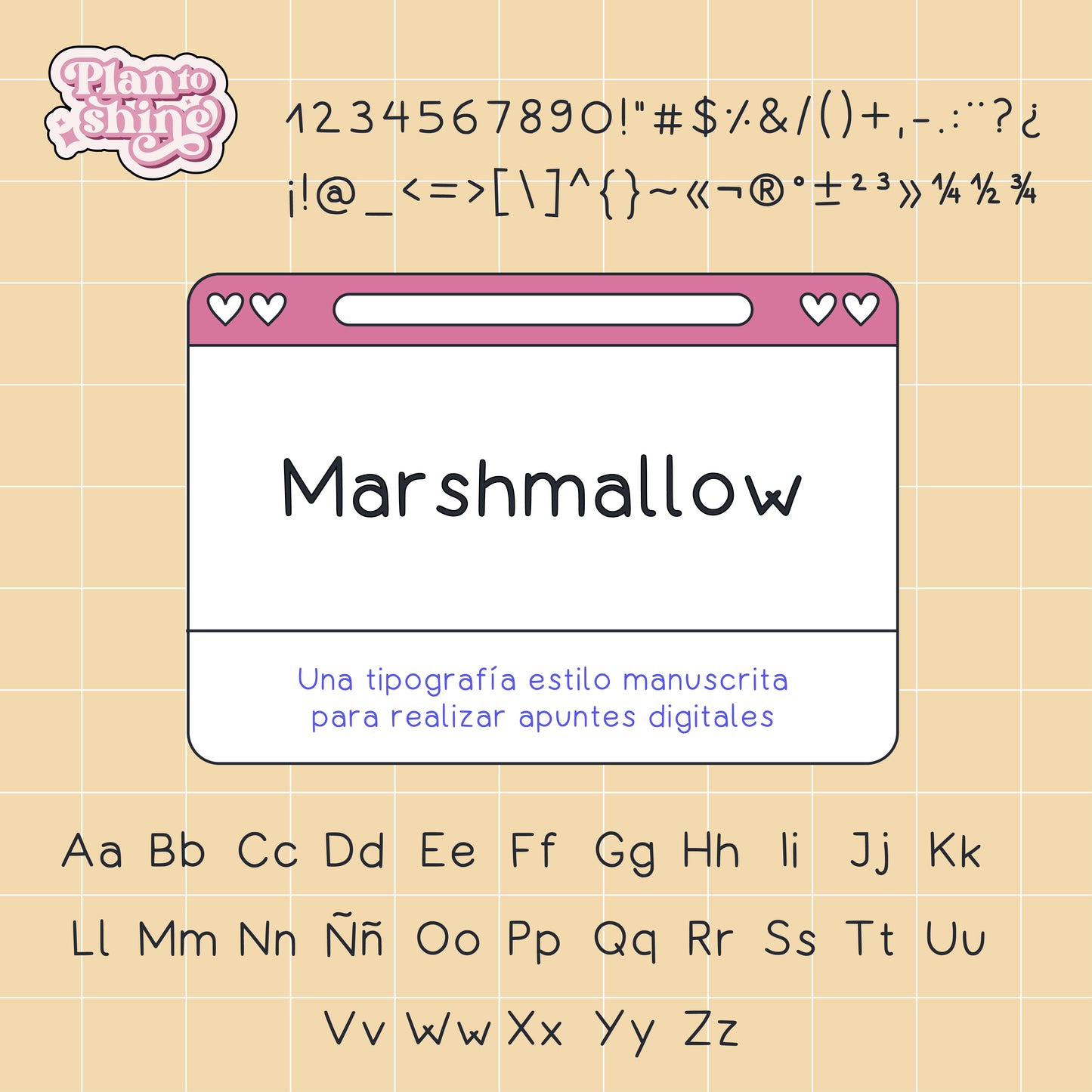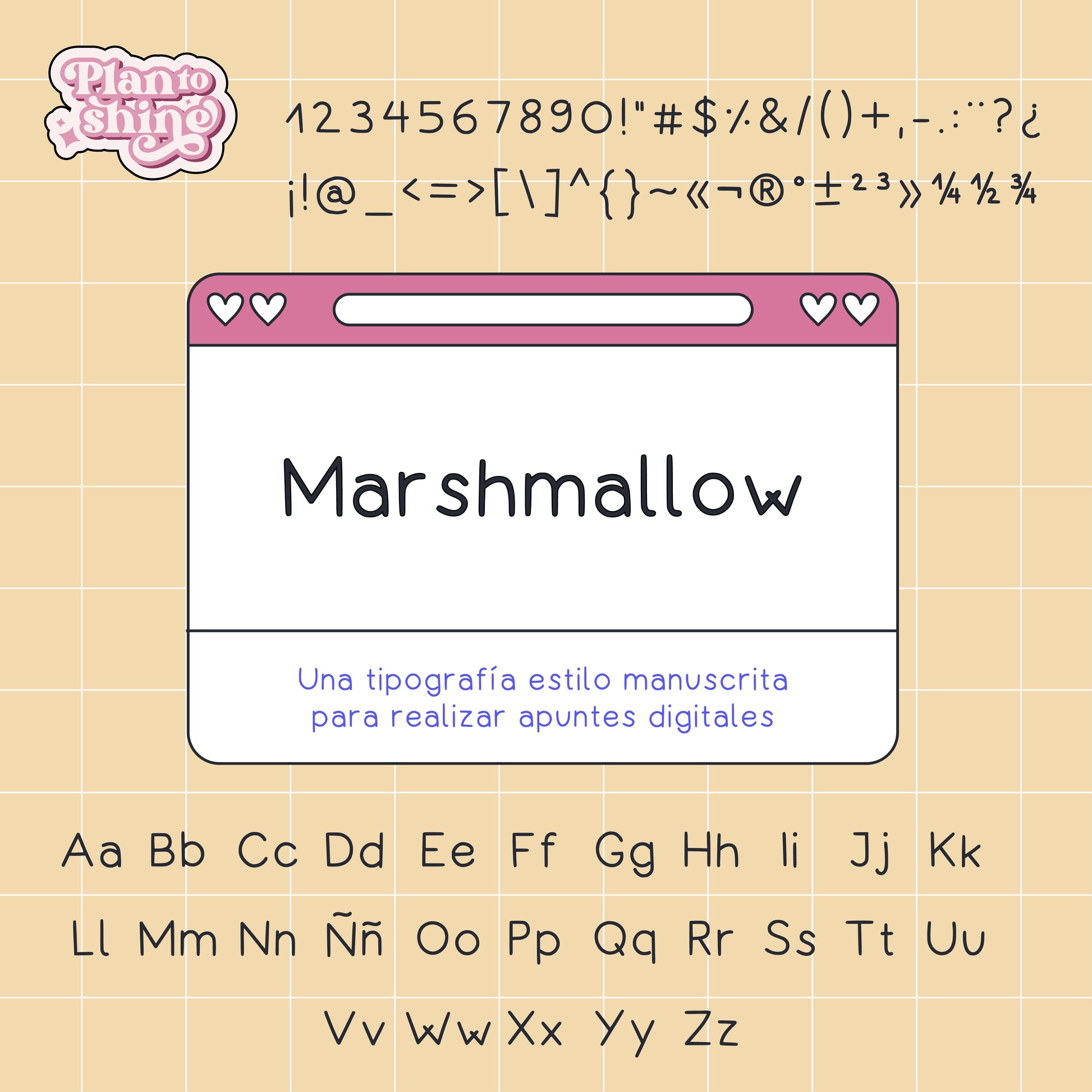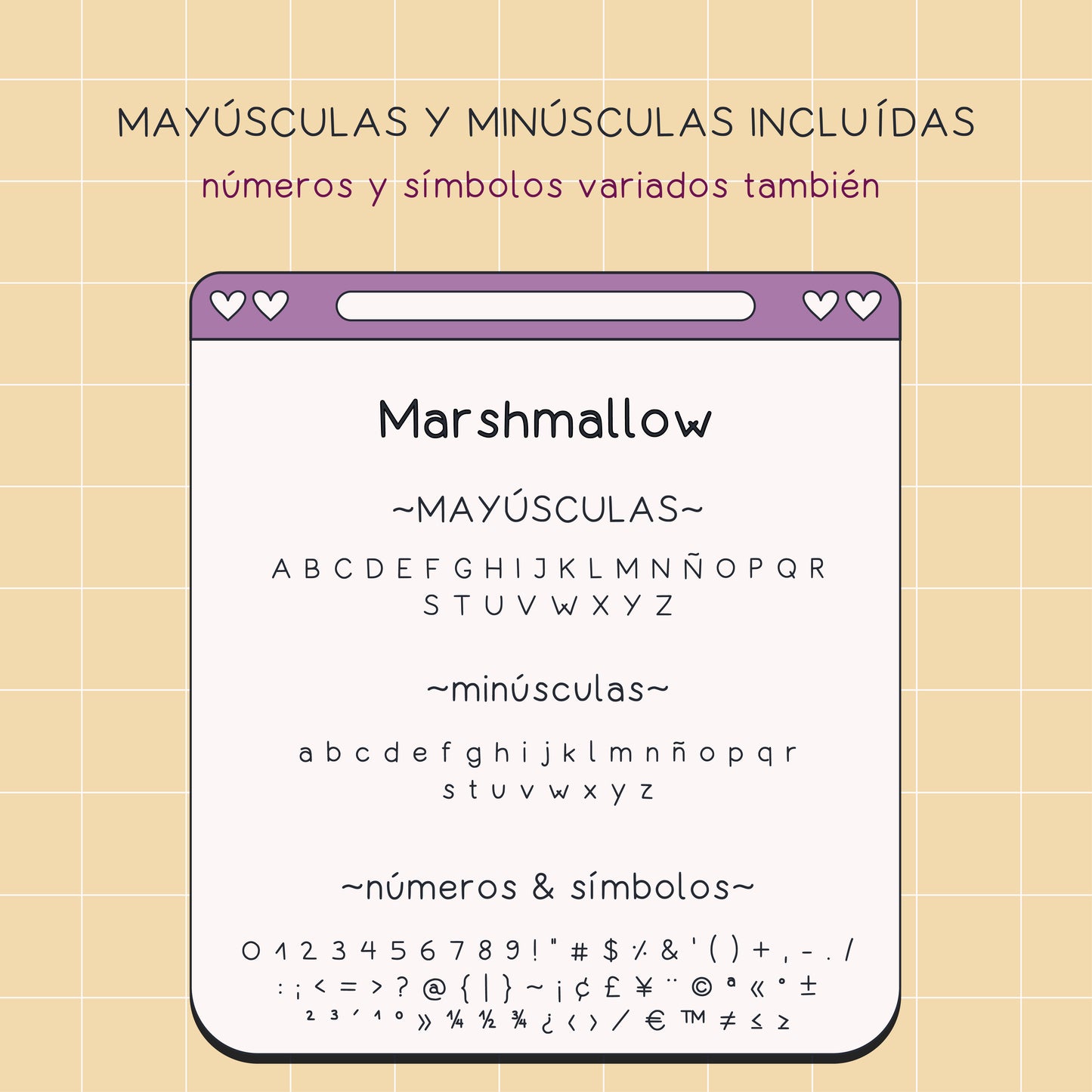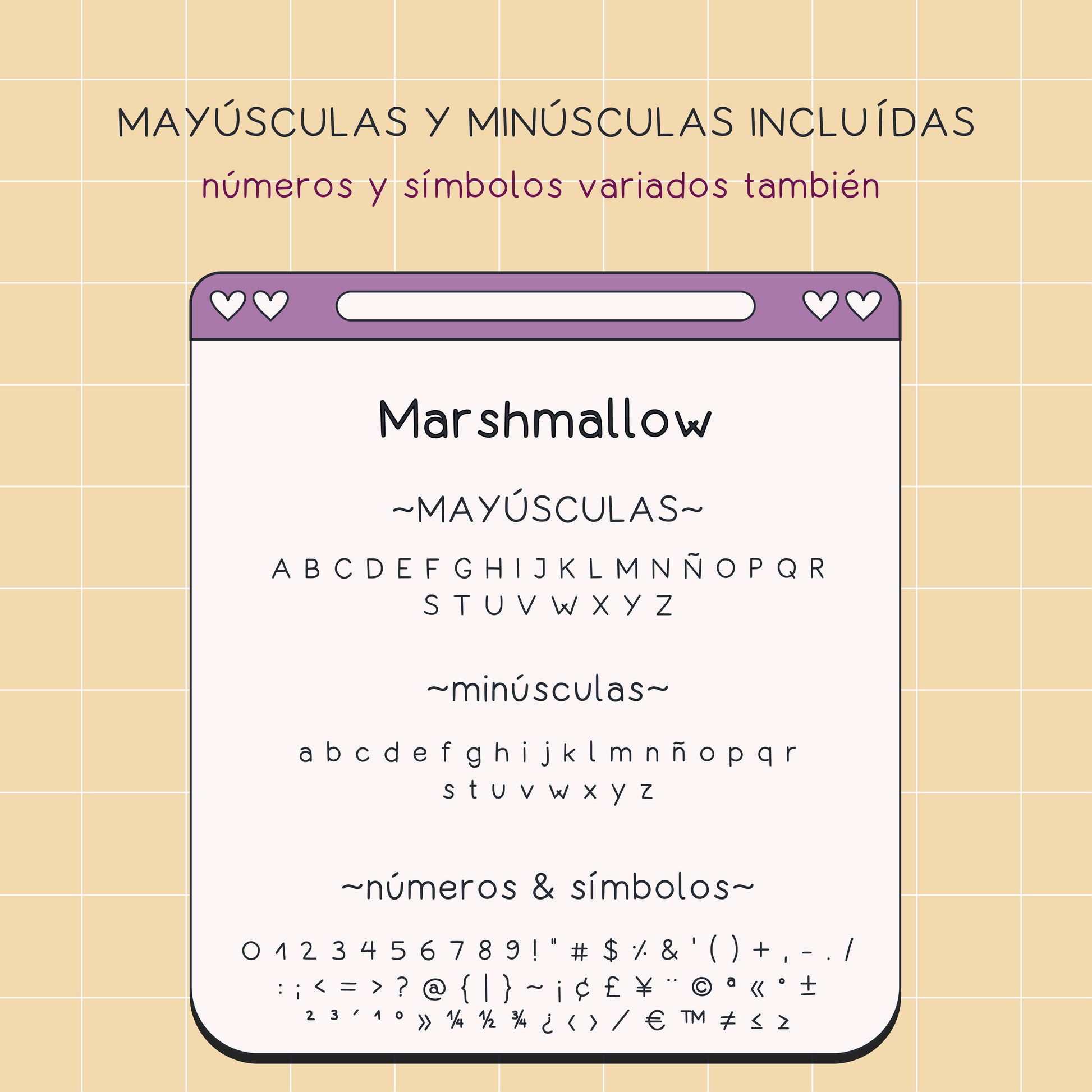
Tipografía Marshmallow
Marshmallow es una tipografía manuscrita suave y minimalista, ideal para crear apuntes digitales claros, bonitos y fáciles de leer. Su estilo handwriting aporta un equilibrio entre simplicidad y personalidad, perfecto para planners digitales, notas de estudio y journaling.
Incluye alfabeto completo en mayúsculas y minúsculas, números y símbolos, permitiendo escribir con fluidez en diferentes proyectos creativos.
Marshmallow es perfecta para quienes buscan una tipografía manuscrita limpia para apuntes digitales, planners y contenido creativo.